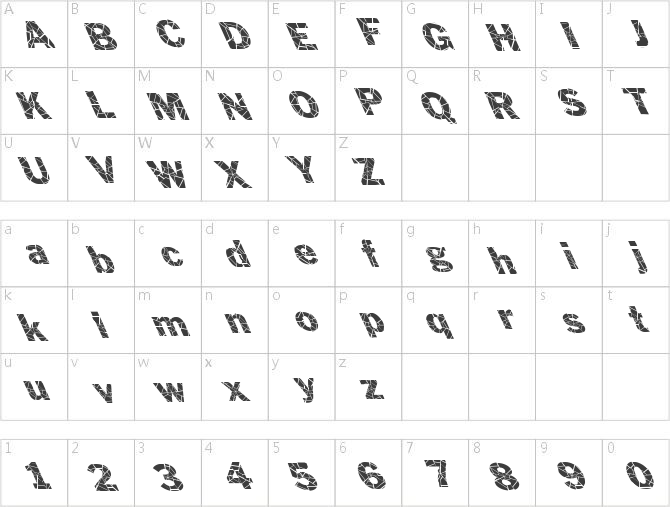
FZ BASIC 56 CRACKED LEFTY
FZ BASIC 56 CRACKED LEFTY介绍
FZ BASIC 56 CRACKED LEFTY字体字库是一款让人赏心悦目、百看不厌的英文字体,适合各类广告和产品包装设计应用,字体大小0.12MB,格式为ttf字体,上传用户是随缘゜,作者/版权方为未知